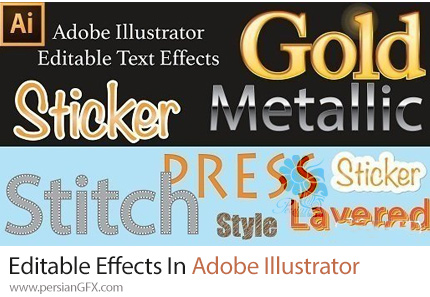
در این دوره آموزشی، من آموزشهای مفیدی را برای ایجاد افکتهای متنی شگفتآور با استفاده از Adobe Illustrator ارائه میدهم. این دوره آموزشی به شما یاد میدهد چگونه افکتهای متنی با استفاده از ایلوستریتور ایجاد کنید. تمام این افکتهای متنی قابل ویرایش هستند و شما میتوانید به راحتی تنظیمات افکت و رنگها را تغییر دهید. بعد از ایجاد افکت متنی جدید، میتوانید به راحتی آن را بر روی هر متنی با استفاده از پنل استایل گرافیکی اعمال کنید. این دوره حتی برای کاربران مبتدی ایلوستریتور مناسب است. من به شما نحوه ایجاد افکتهای متنی را به شما گام به گام نشان خواهم داد. با گذراندن از این دوره، اصول ایجاد افکتهای متنی قابل ویرایش را درک خواهید کرد و نتیجتاً قادر خواهید بود که افکتهای متنی خود را ایجاد کنید و ترکیبهای مختلفی را بسازید.
شما خواهید آموخت که چگونه افکتهای متنی زیر را ایجاد کنید:
- افکت دستنوشته
- افکت فلزی
- افکت شبیه به استیکر
- افکت فشرده
- افکت طلایی
- افکت دوخته شده
- افکت لایهبندی شده